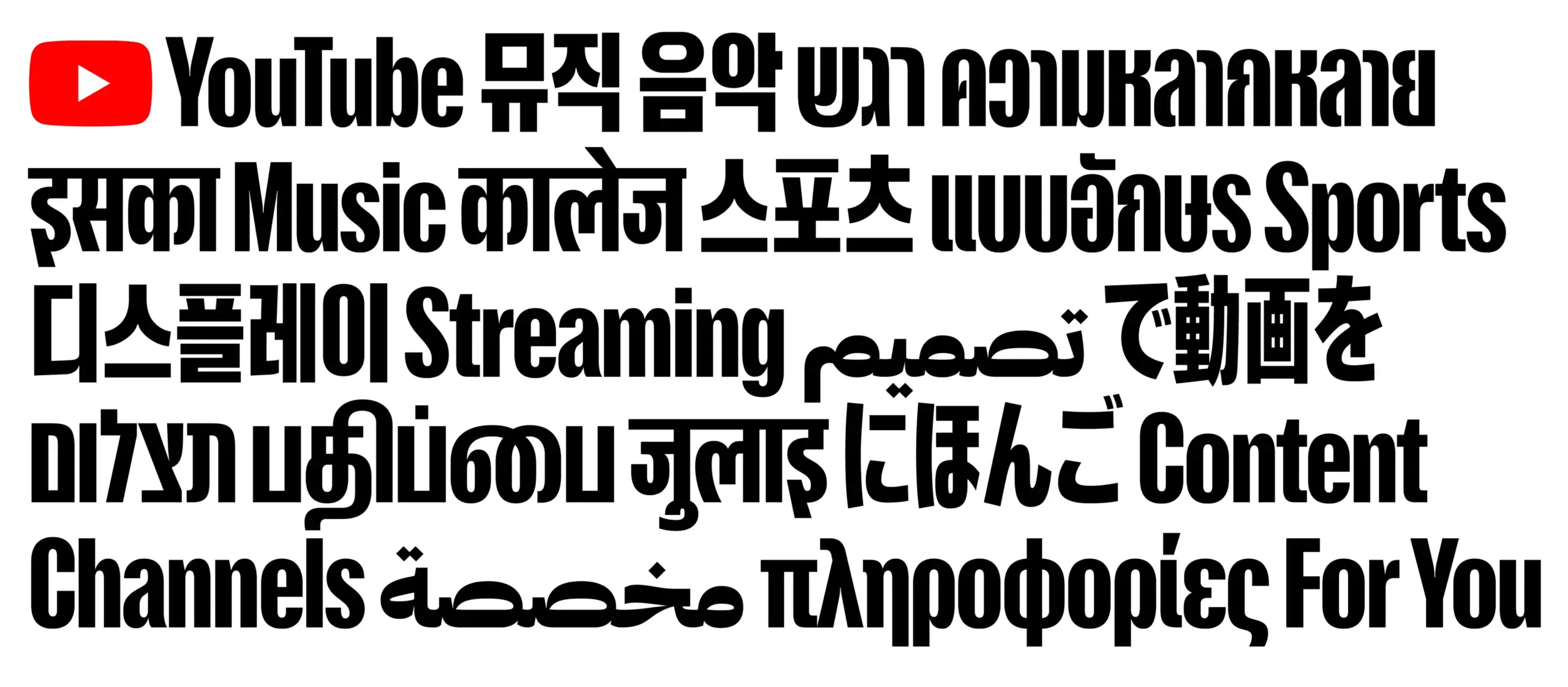
YouTube Display, de Sharp Type, una tipografía multiscript de alma global
Devanagari, tamil, hangul, tailandés, hebreo, árabe, japonés, cirílico y latino, nueve sistemas de escritura para dar una respuesta global a un proyecto que llega a todos los rincones del mundo. YouTube es una de las plataformas más populares a nivel planetario y su identidad visual debe ser acorde a su alcance.
Y no existe herramienta para unificar una marca de la envergadura del gigante del vídeo en línea como una tipografía diseñada a medida; una tipografía, además, que tuviera la capacidad de conectar con personas provenientes de los más diversos entornos culturales.